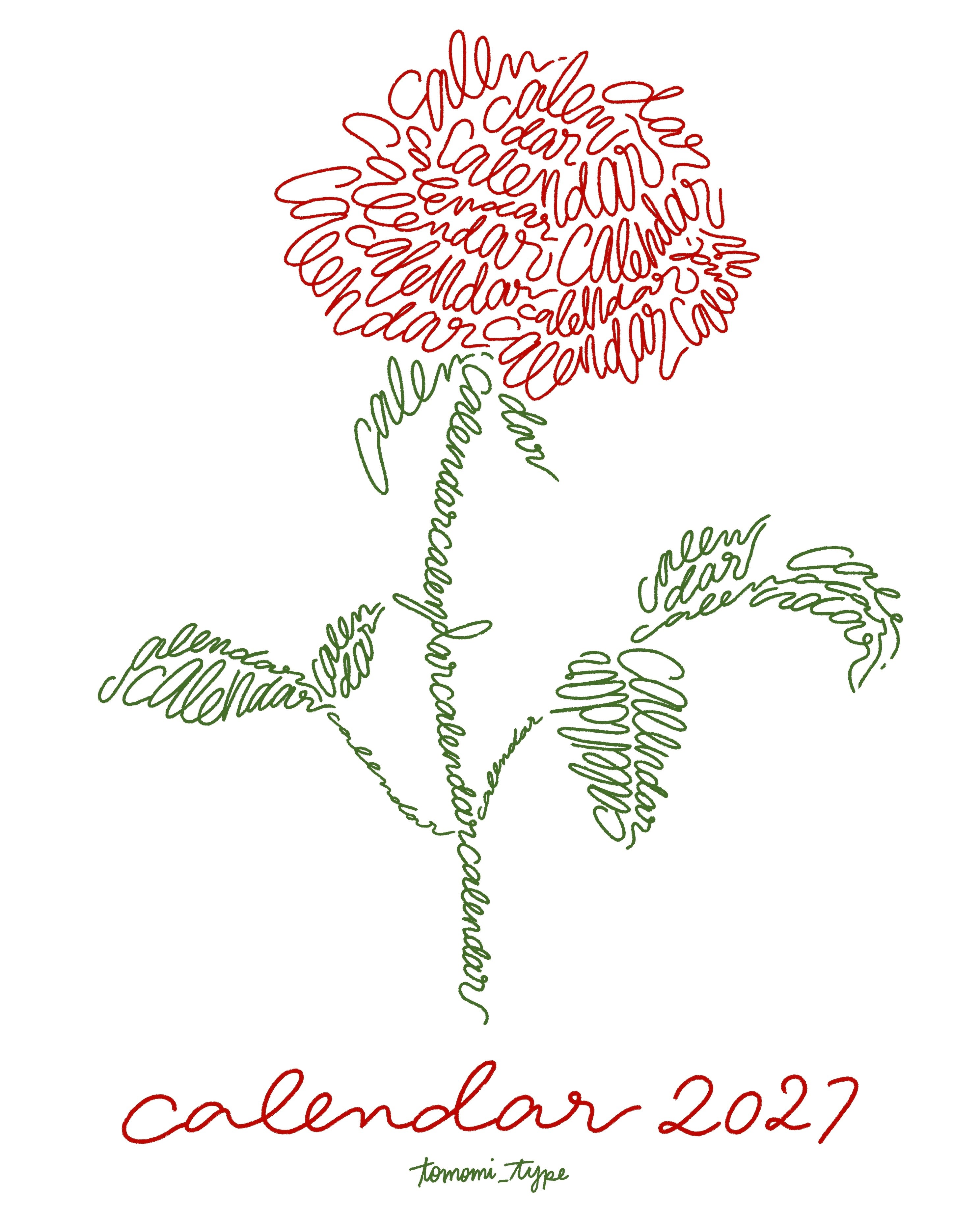
文字で描いたお花のカレンダーを販売します!
words flowerは、文字だけで描いたお花です。
今回なんとカレンダーにしました!
その月の誕生花を描いています。
【1月】スイートピー
【2月】アネモネ
【3月】チューリップ
【4月】アルストロメリア
【5月】カーネーション
【6月】アジサイ
【7月】トルコキキョウ
【8月】ヒマワリ
【9月】ダリア
【10月】ガーベラ
【11月】ユリ
【12月】バラ
※誕生花には諸説あります。
名前の通り、文字で描いた花のステッカーです。